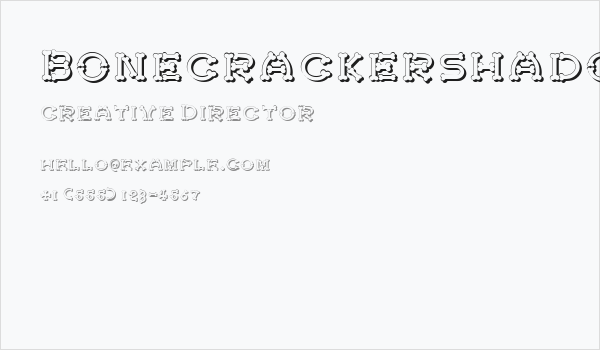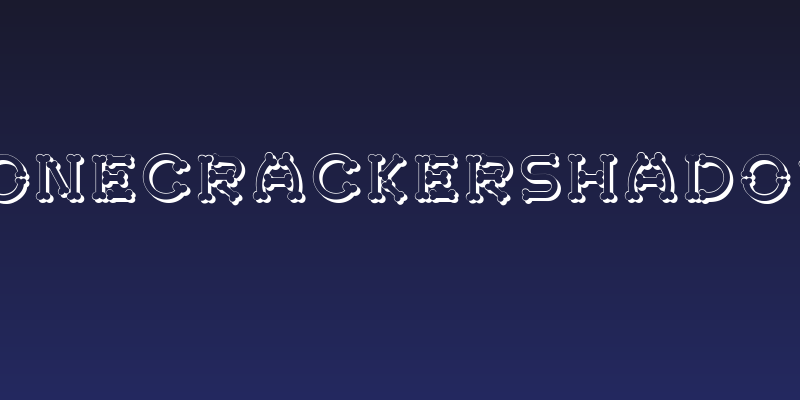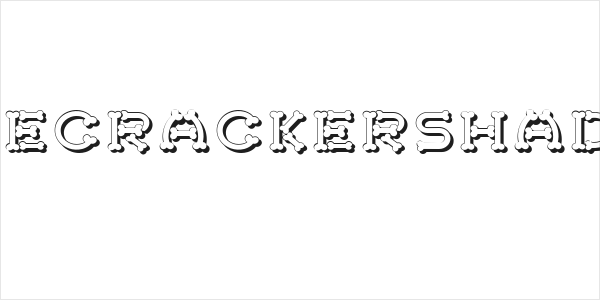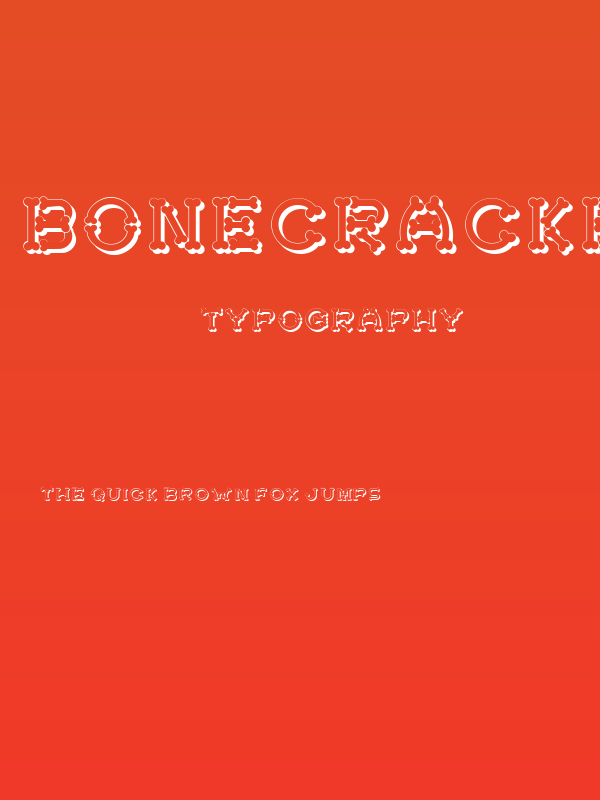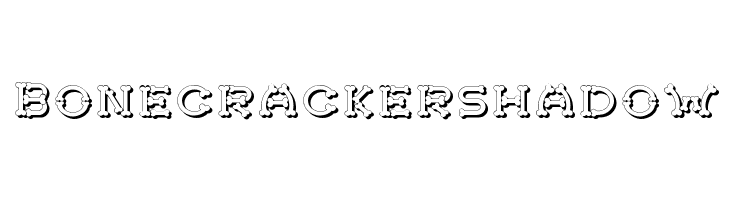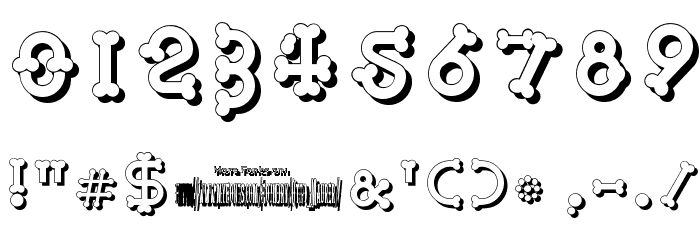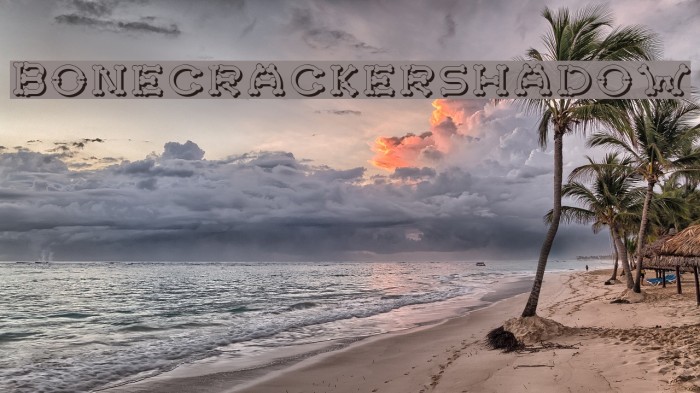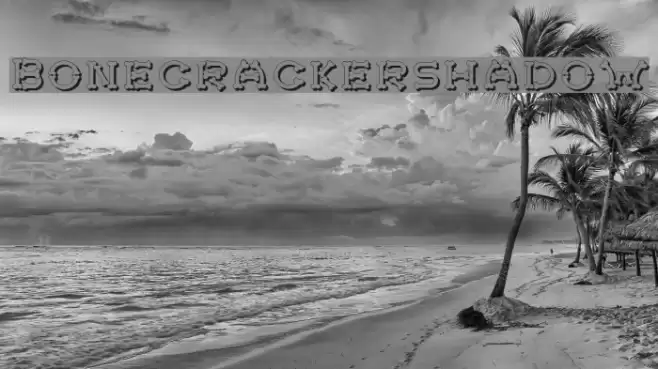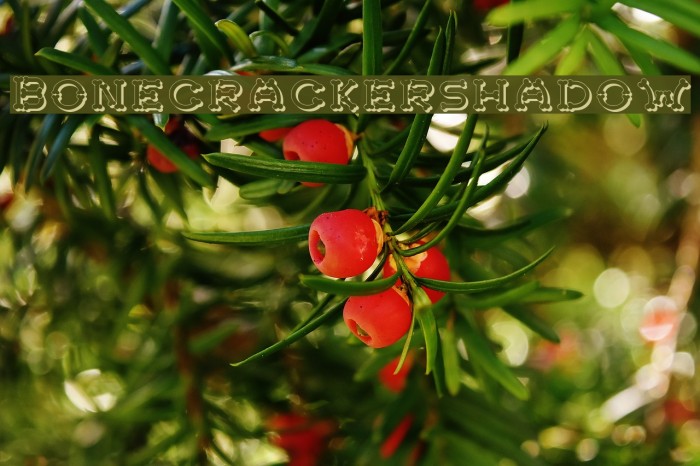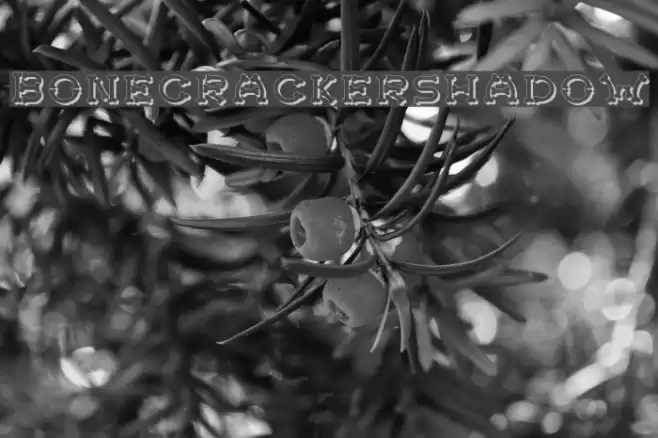
Bonecrackershadow Font
✎ Decorative
| Proyectos propuestos | Ideal for Halloween-themed projects, party invitations, horror movie posters, or any design requiring a quirky, eerie touch. |